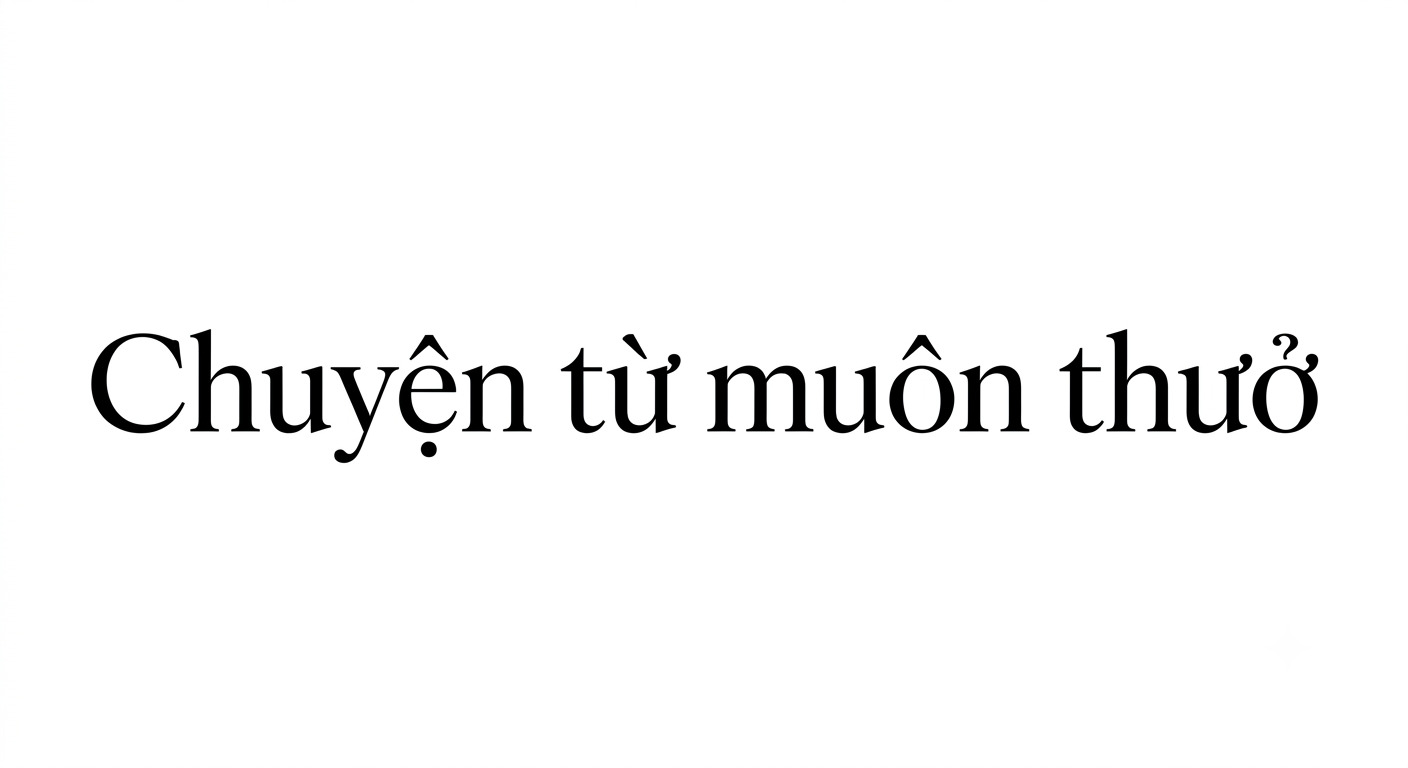
Font Ogg là gì?
Font Ogg là một bộ phông chữ thuộc dòng Calligraphic Serif (chữ có chân mang hơi hướng thư pháp) được lấy cảm hứng từ các tác phẩm nghệ thuật chữ của nhà thiết kế sách nổi tiếng thế kỷ 20 – Oscar Ogg. Điểm đặc trưng của phông chữ này là sự hòa quyện giữa các đường nét chạm khắc thời kỳ Phục hưng và phong cách thư pháp La Mã uyển chuyển. Bộ chữ sở hữu độ tương phản sắc sảo giữa nét thanh mảnh mai cùng nét đậm vững chãi, tạo nên vẻ ngoài kiêu kỳ, mang đậm tính thời trang và nghệ thuật biên tập cổ điển.
Trong lĩnh vực thiết kế thương hiệu đương đại, Ogg thường được các nhà mốt xa xỉ, thương hiệu nước hoa, trang sức và mỹ phẩm danh tiếng lựa chọn làm điểm nhấn thị giác. Tuy nhiên, các nét chữ nghiêng và đường cong uốn lượn của bản gốc quốc tế thường bị lỗi khi gõ dấu tiếng Việt, khiến các ký tự có dấu mũ hay dấu thanh bị lệch trục thẩm mỹ. Bản Việt hóa do In Viva chọn lọc đã được tinh chỉnh tỉ mỉ từng dấu thanh tiếng Việt, giữ nguyên vẹn tỉ lệ thanh lịch của bộ chữ gốc mà không làm đứt gãy cấu trúc chữ khi dàn trang.
Lưu ý: Nét thanh của Font Ogg rất mảnh mai và tinh tế. Khi thiết kế tiêu đề trên bề mặt giấy tối màu, bạn nên phối hợp kỹ thuật ép kim nhũ vàng hoặc nhũ bạc để các đường cong nghệ thuật của phông chữ nổi bật sắc sảo.
5 ứng dụng Ogg Font Việt hóa trong thiết kế và in ấn
Nhờ phong cách thanh lịch, giàu tính nghệ thuật và mang hơi hướng cổ điển, Ogg Font Việt hóa được ứng dụng linh hoạt trên nhiều sản phẩm bao bì và quà tặng doanh nghiệp:
- Thiết kế bao bì hộp cứng mỹ phẩm và nước hoa: Ogg phù hợp để thể hiện tên thương hiệu trên hộp giấy Ivory, giấy mỹ thuật hoặc hộp carton lạnh. Khi kết hợp cùng kỹ thuật ép kim, dập nổi hoặc phủ UV định hình, font chữ giúp tạo điểm nhấn tinh tế cho các dòng sản phẩm cao cấp.
- Sản xuất bao bì hộp yến sào và quà tặng sức khỏe: Các đường nét mềm mại của Ogg khi in trên hộp quà, hộp trà hoặc sản phẩm chăm sóc sức khỏe giúp thương hiệu thể hiện sự trang trọng, phù hợp với các dòng quà tặng dành cho khách hàng và đối tác.
- In ấn thiệp mời sự kiện và ấn phẩm thương hiệu: Font Ogg phù hợp để sử dụng cho tiêu đề thiệp mời, catalogue, voucher hoặc brochure. Kiểu chữ giàu tính thẩm mỹ giúp các ấn phẩm truyền thông tạo được dấu ấn riêng trong các sự kiện doanh nghiệp, triển lãm hoặc chương trình đặc biệt.
- Gia công nhãn chai rượu vang và sản phẩm thủ công: Ogg có thể kết hợp cùng giấy mỹ thuật, giấy kraft hoặc tem nhãn cao cấp để tạo phong cách sang trọng cho các sản phẩm như rượu vang, nến thơm, cà phê hoặc đặc sản quà tặng.
- Trang trí túi giấy thương hiệu thời trang: Logo sử dụng Ogg trên túi giấy Ivory, giấy mỹ thuật hoặc túi Kraft giúp thương hiệu thể hiện phong cách tinh tế, phù hợp với các dòng sản phẩm thời trang, phụ kiện và quà tặng boutique.
5 lưu ý khi sử dụng Ogg Font Việt hóa
Để font Ogg giữ được vẻ đẹp thanh lịch khi đưa vào sản xuất thực tế, designer cần chú ý các yếu tố kỹ thuật sau:
- Kiểm soát độ mảnh của nét chữ: Ogg có sự tương phản rõ giữa nét thanh và nét đậm. Khi sử dụng trên tem nhãn nhỏ hoặc sản phẩm có kích thước in hạn chế, nên kiểm tra kích thước chữ để hạn chế tình trạng mất nét trong quá trình in.
- Tối ưu đường Path cho gia công dập nổi: Khi sử dụng Ogg làm logo trên hộp quà cao cấp, file vector cần được xử lý các điểm giao nhau và đường cong nhỏ. Việc tối ưu path giúp khuôn dập tái hiện rõ chi tiết chữ, hạn chế ảnh hưởng đến bề mặt giấy trong quá trình gia công.
- Lựa chọn kỹ thuật in phù hợp: Ogg phù hợp với các phương pháp như ép kim, in UV, phủ UV định hình hoặc in Offset chất lượng cao. Với các chi tiết chữ mảnh, nên kiểm tra mẫu thử trước khi sản xuất số lượng lớn để đảm bảo hiệu quả hiển thị.
- Điều chỉnh khoảng cách ký tự (Kerning): Với những cụm từ tiếng Việt có nhiều dấu thanh, designer nên cân chỉnh khoảng cách giữa từng ký tự để bố cục logo và tiêu đề cân đối hơn, tránh tình trạng các nét chữ bị chạm vào nhau.
- Convert font trước khi gửi xưởng: Trước khi xuất file sản xuất, nên thực hiện Create Outlines để chuyển đổi chữ thành vector. Điều này giúp hạn chế lỗi thiếu font hoặc thay đổi kiểu chữ khi mở file trên hệ thống thiết kế và máy in.